大多数人最开始学会书写的汉字,一定都是自己的名字。随着年龄的增长,书写自己名字的机会越来越多。签名作为个人身份的代表,能体现一个人的个性特征。选择一款合适的字体,能适用于各种场合,使得观看着抽象地产生对自然万物的美好联想。今天要给大家介绍的就是几款使用在签名上大放溢彩的字体。
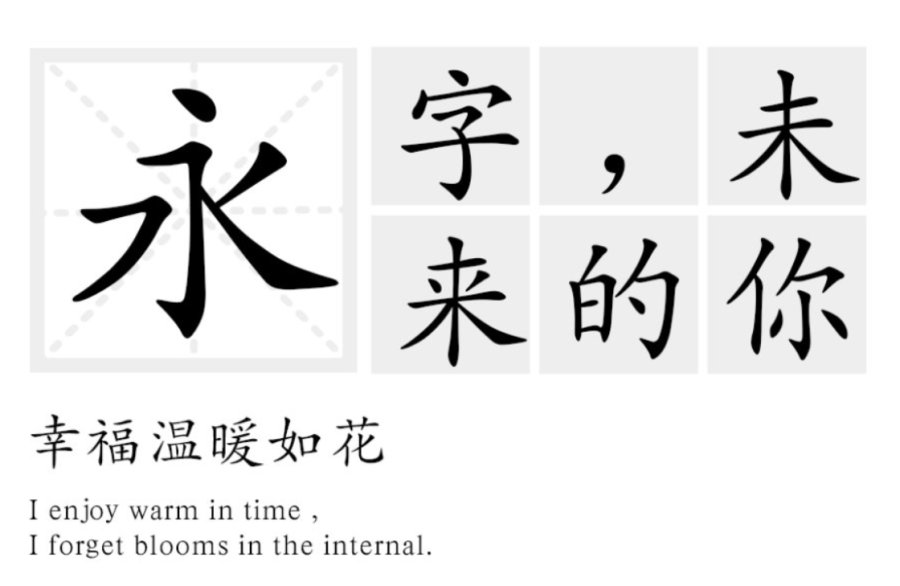
印研所正楷体:这款字体的特点是:横划倾斜,竖划斜直不一,笔划粗细有起伏,笔形流畅、自然、规范、标准,结构稳重,是传统书法艺术的一种享受,也是初学汉字的首选字体。字形清晰,便于看图片识别字体、端庄大气。
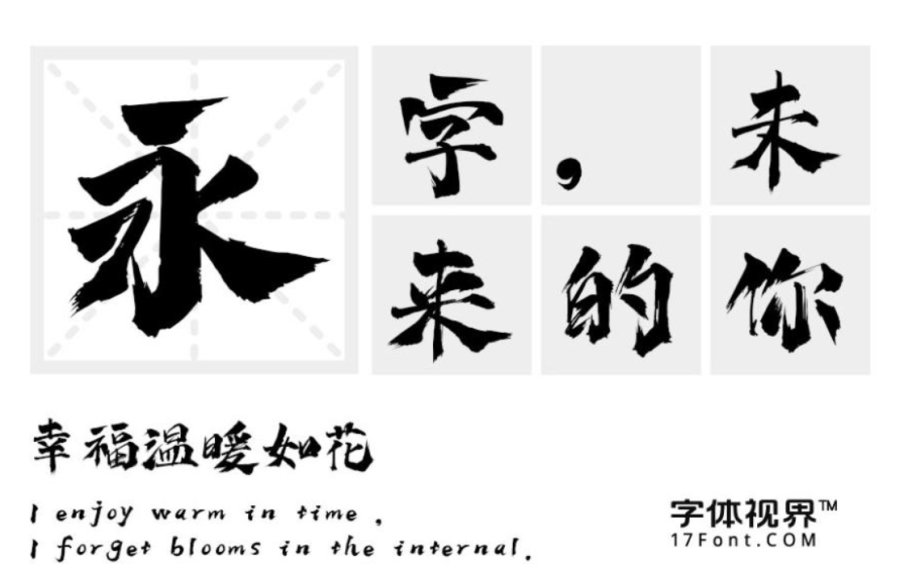
上首疾风体:这款字体风格锐利,钝点强力,夸张的笔锋增添了字体的活跃性,而且字体中粗细衔接,使字体显得生动。作为签名字体,洒脱大气,浑然天成。还适用于封面设计、logo设计、广告、影视等领域。
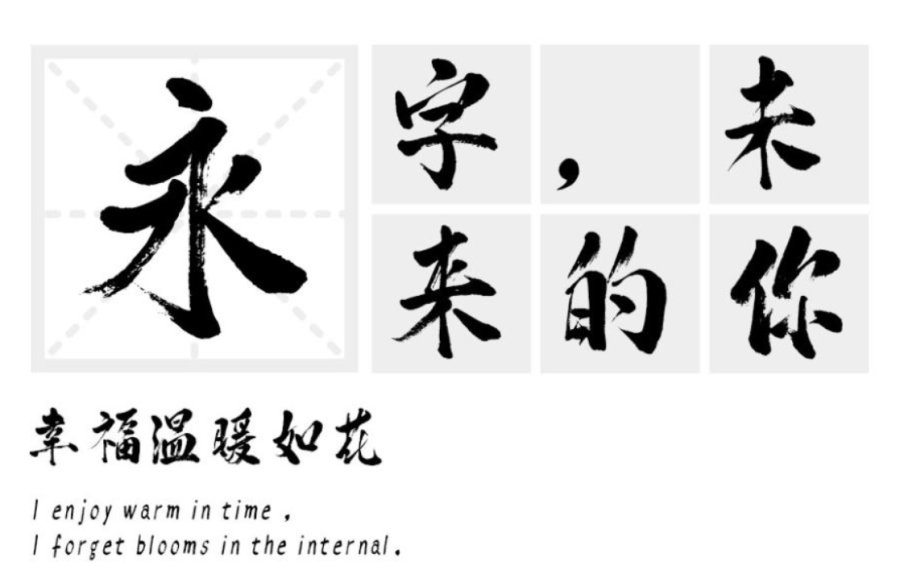
汉标高光毛笔字:这张字体图片展现出了书法手写体的风韵,楷书味道浓厚,由于字体较大,使得笔画清晰度较高,笔画中也减少了过多的处理和笔势,厚重、饱满。因为是纯手写的原因,它独特的气质更与其他字体不同,看似统一,其实各有各的味道,每个字都可以独具风情。有一种浑然天成的潇洒感。